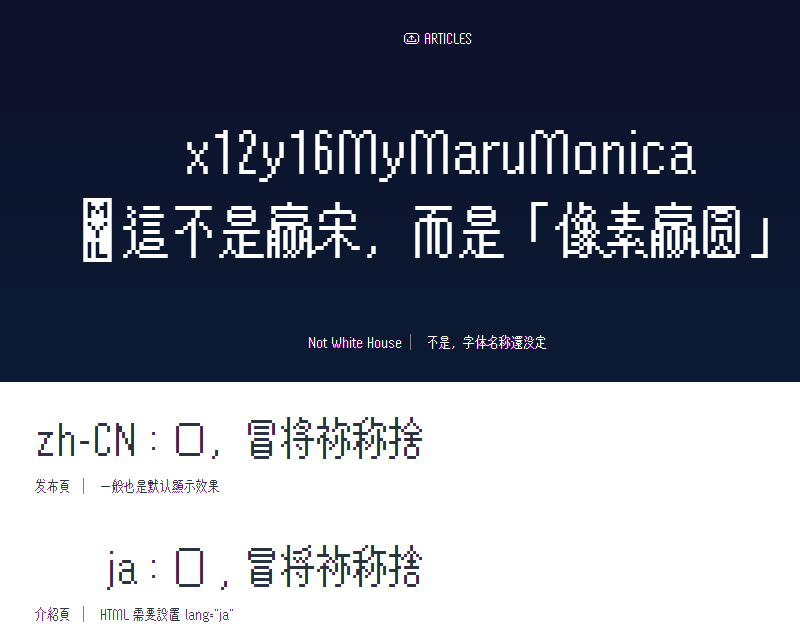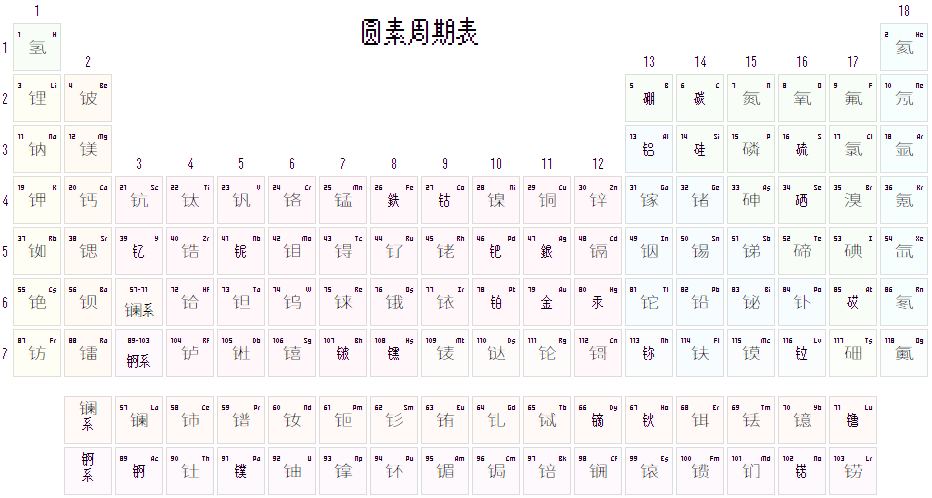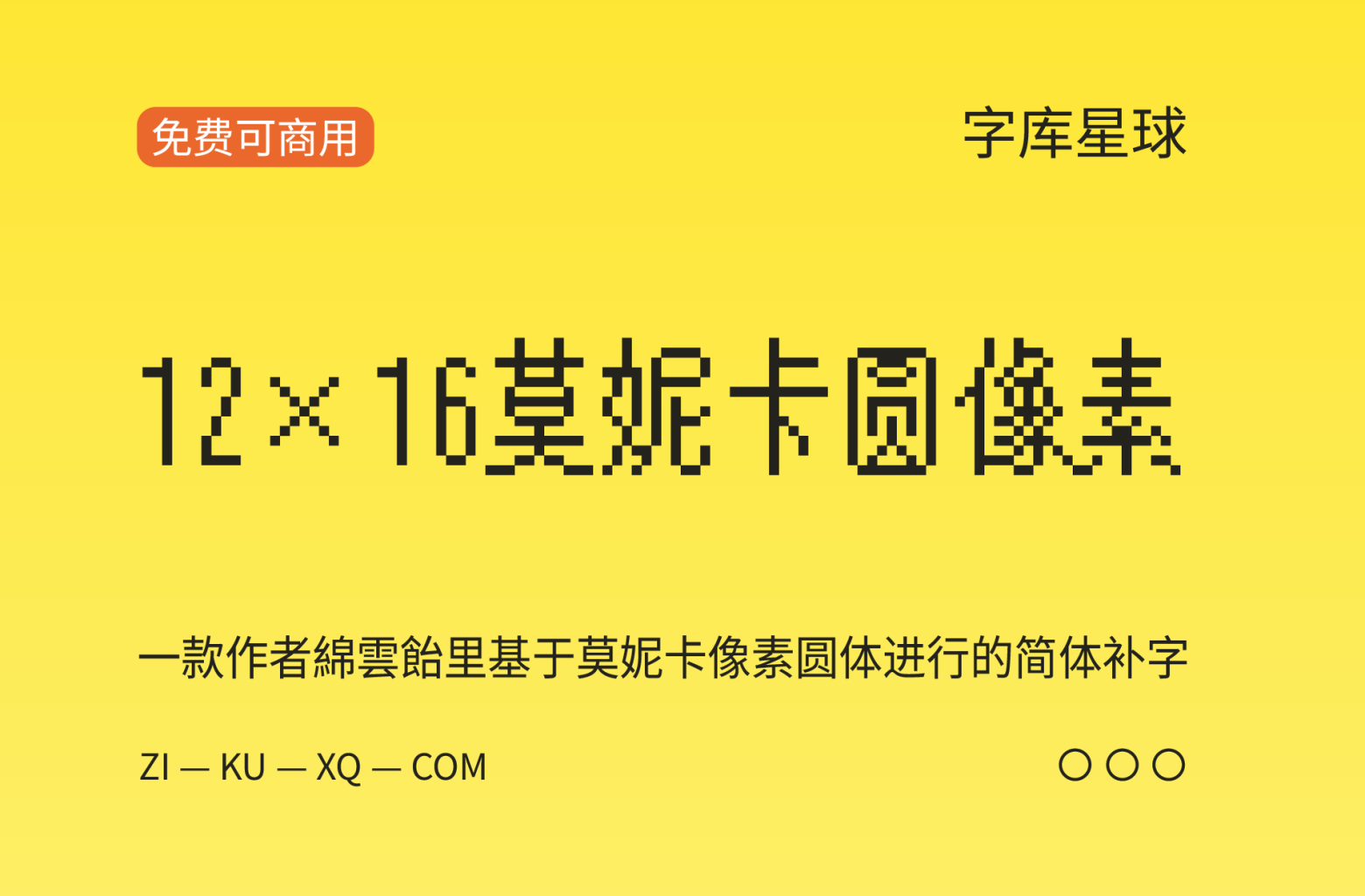
12×16莫妮卡圆像素是一款作者綿雲飴里基于莫妮卡像素圆体(x12y16pxMaruMonica)进行的简体字补充的免费可商用字体。
某日本像素游戏用到了像素字体“x12y16pxMaruMonica”,其特点为12×16的窄圆体,汉化组甚至找不到类似的中文像素字体。
注:虽说是“像素”字体,但原作不含点阵,字形实际是矢量勾勒像素块,使用时需将字号设为16px的整数倍以取得锐利像素效果。
看了汉化文本缺字统计,我觉得只缺六百多字的话,今年内应该是可以补完的,于是先做了个临时预览版(截至 Ver2025-5-30 只做了3百字,其它几百暂用类似日标字顶替,如“绘”,繁体为“繪”,我用“絵”),提前放出是吸引感兴趣的人参与补字。
与原作的差异
“绘、絵”尚且码位不同,而日文的“冒(冒,U+2F8D2)、将、称、捨”等字与中文码位完全一致,字符上不能区分,于是我在保留原作字形、字序的前提下,在尾部追加了中式字形设为默认,给原字体字形添加了locl
OT特性以备日区环境调用,例如浏览器遇到lang="ja"
即可切换为原日式字形。
我感觉原作逗号做错了,但仍保留,并另作一个“中式逗号”
还额外添加了liga
calt
特性用于中文标点,例如在前述游戏里文字有勾边,原字体的破折号,眼尖的玩家能看见中间有断开,本改版则绝不会断:因为用liga
将“——”替换为1个字符“⸺”
虽然我希望对原作无损修改,但其实改动了一个字:口。原作里口囗完全一致无法区分,考虑到“口”占太满就上下缩小1像素,将“囗”设为口的日区字形。
“傻瓜偏旁”
也许有人要问,相比其它人的,本字补字有什么优势?我为此字研了一个技术:傻瓜偏旁。
新款造字软件如Fontra,对造中文有个奇妙的支援,是可变字体引申出的功能“智能偏旁”,比如在预先做好某偏旁最宽最窄两极端之后,就可以无级调节宽度、在所有包含此偏旁的汉字里复用它。
但像素字体不存在无级调宽——一般不许0.25个像素——我只能很傻瓜地预制了偏旁的每个需要的宽度字形以备复用。而且ttf复用字形几乎不占文件体积,这导致我的字体比原作.ttf体积还小。
参与补字者可以直接用预制偏旁肆意拼字,想想就爽🤪
截至 Ver2025-5-30,以下这3百字我已经做好了:
业丢丰为么乡亚产亻亿仅份伙伟伲你侣俏俭倘偌偷內关冒击刨别剑办劳卡卫厅历厉压发叠另叹吆吓吔吗吧呃呕员呢呯咂咔咕咻哆哎哟哪唉唬啊啥啦啪啰啵喻嗑嗙嗯嘀嘎嘞嘟嘿噗噜噢噼圆圾坭垃垫增够夺奶她妇妈妞妪妮姘婊娆宁审宫对寻导将尔尘师帕帜帮庞开归录徜⺖忆怄怔恘您惝憋懂户扌扔扩扫扭扯抠抳拖拼挖挡挣挪捡捨掿揍揭搞摁撑撬撸擙时术权极枙柅查桌检棵椤橹欢步殂殓每⺡汉沉沤涉渴澈灭灵灾炽烤烫热爱爸牜牠牺狍狔狰猡獐玛电疗疛瘾盯盼睁睑瞌矿码砍砰砸砹硒硷碰碳磕祂祎祢秜积称窣窸筷粑糕糬纟纣级纬纽织绳缟罗职脖脸腌荧营虵虾蜇蜕蝇螃蟑衬裆裱讠订认讦讳讴证诂评识诤该说诶诺课谕谤谪赠赢赶趟跑踫蹭躺边过违逛邓钅钇钉钦钬钮钯钴铂铇铌铐铛铝铮销锐锕锘锣镐镑镝镤镥门阂队阳险韧饣饮饱饼馃驭驰驱驹骇骈验鲁鿭𪠽𫇦𫟷𬭛𬭶𰕎⋯⸺︐︑︒︓︔,﹁﹂▮⁃⺅⺉⺒⺓⺕⺘⺨⺩⺫⺭⺰⺼⺾⻁⻂⻄⻈⻉⻊⻌⻏⻐⻖⻙⻠⻢⻪⻰
另外,还补充了多重映射:⤹⤸ⒶⒷⓍⓎ⮹⨂⊚🟗🟕⌨⊝⨁➖➕⌂,这几个是原作就有字形但放私用区的。原作中特地放私用区的游戏符号皆在本作中保持一致。
晩(晚)像素里不必区分也合并映射了,但如果你游戏里故意要区分这2字请告诉我。
以下这些字是游戏汉化用到,也是我未来待补的:
专东丝两严丧临丽义乐习书买亏亲仓仪们仿优传伤侧俩值倾储兴养兽冻净减凯划则刚创剂剧务动劲势华协单卖厌厕变启呜响唤啃喷园围图圣场块坚坟坠墙壳壶处备复头奋娇实尝层岛币帘带库应废异张弹强彻德怀态总恶恼悬惊惫惯懒战扑执护报拟拥择挤挥捞损换掷搁搅摄摆摇攒敌显晕暂朵杀杂构枪标栏树样桥毕汇沟泽浆浇测浑浓涂涨渍渐渗溃满滤滨滩濒灿烁烂烦烧牵猎环现皱盐监盘础确离种稳竖竞笔笼筛签简篮类紧红约纪纯纳纵纸纹线组细终绊绍经绒结绕绘给绚络绝统绣继绪续维绵综绿缓编缚缝罚罢联聪肃胀胜胶脏脑腻腾舱艳艺节苏茧荡药获萝蓝虑虽蚀蜡补袭见观规视览觉计讨让议记讲讶许论设访诅诉词试诚话诞诡详语误请读谁调谈谏谓谜谢谣谧谨谱贝负贡责败货质贩贪贬购贮贴贵费贺资赋赌赎赏赛跄躲车轨转轮软轻较辈辉输辽达运还这进远连迟适选逊遗邻酱酿释鉴针钢钱钻铁银链锁错键镇镜长闪闭问闲间闹闻阅阔阙阴阵阶际陆隐难雾页顶项顺须顽顾顿预领频颓颗题颜额风飘飞饥饭饰饲饿馅馆馒马驶驾骂骄骚鱼鲜鲨鲸鳍鳗鸟鸣鸦齿,目前应汉化组之急先拿日式字替代。
至少元素周期表远远不全……期待大家参与